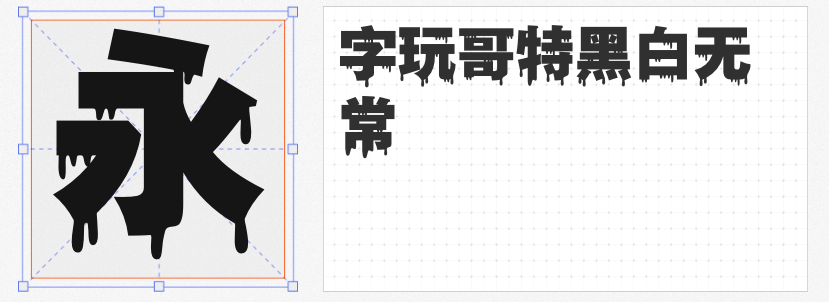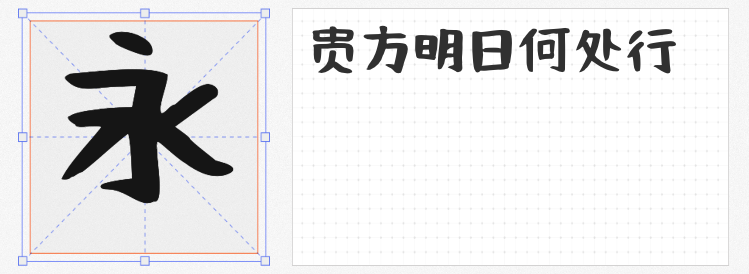
在创意设计中,字体不仅是信息的载体,更是视觉氛围的塑造者。今天为大家推荐四款风格独特且可免费商用的创意字体,它们各具特色,能轻松适配游戏、海报、品牌包装等多元场景,让你的设计脱颖而出!
这款字体从哥特艺术中汲取灵感,以阴森、诡异、恐怖为核心风格。字形中融入不规则血滴元素,笔画粗犷且带有撕裂感,仿佛暗夜中的幽灵低语。无论是游戏海报、恐怖主题影视宣传,还是万圣节活动物料,它都能瞬间营造出紧张刺激的氛围,让观众一秒入戏。
厌倦了千篇一律的印刷体?这款手写字体以自然随性的笔触打破僵局。笔画圆润灵动,仿佛孩童涂鸦般充满童趣,却又不失专业设计的精致感。无论是儿童品牌、餐饮包装,还是社交媒体文案,它都能为作品注入亲和力,让信息传递更温暖、更生动。重点是——完全免费商用,性价比拉满!
若需一款兼具稳重与张力的字体,飞波正点体是不二之选。笔画厚重有力,结构紧凑,气势上扬,尤其适合作为标题大字。无论是电影海报的冲击力呈现、电商促销的醒目标语,还是品牌名称的视觉强化,它都能以强烈的存在感抓住眼球,让设计瞬间“立住”。
这款字体以“柔软”为关键词,字形圆润Q弹,仿佛会呼吸的橡皮泥。笔画粗细对比强烈,书写自由洒脱,既有软笔书法的灵动感,又充满现代设计的趣味性。无论是儿童绘本、文创周边,还是年轻化品牌包装,它都能为作品增添温暖亲切的氛围,让人一眼爱上。